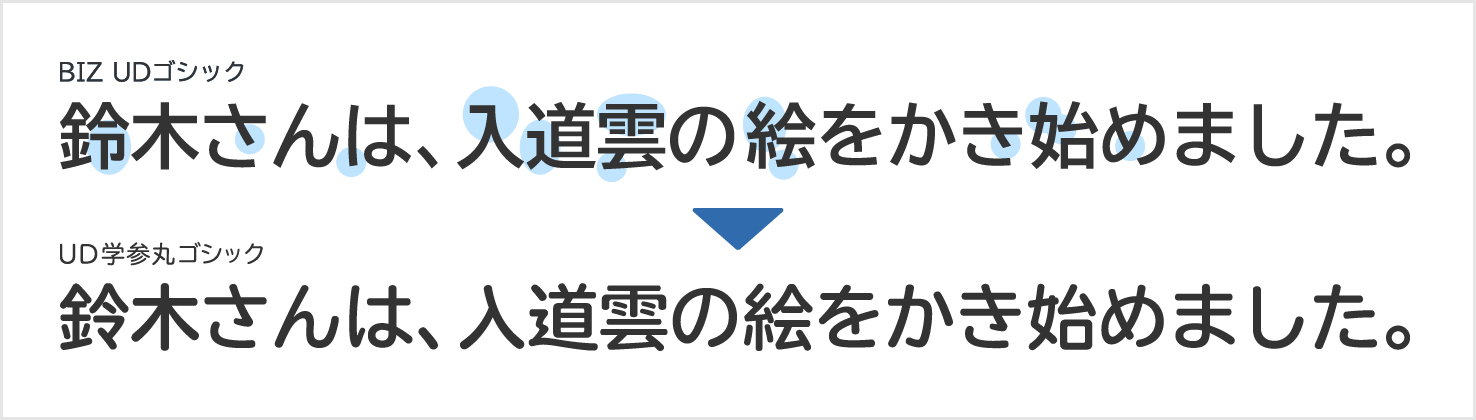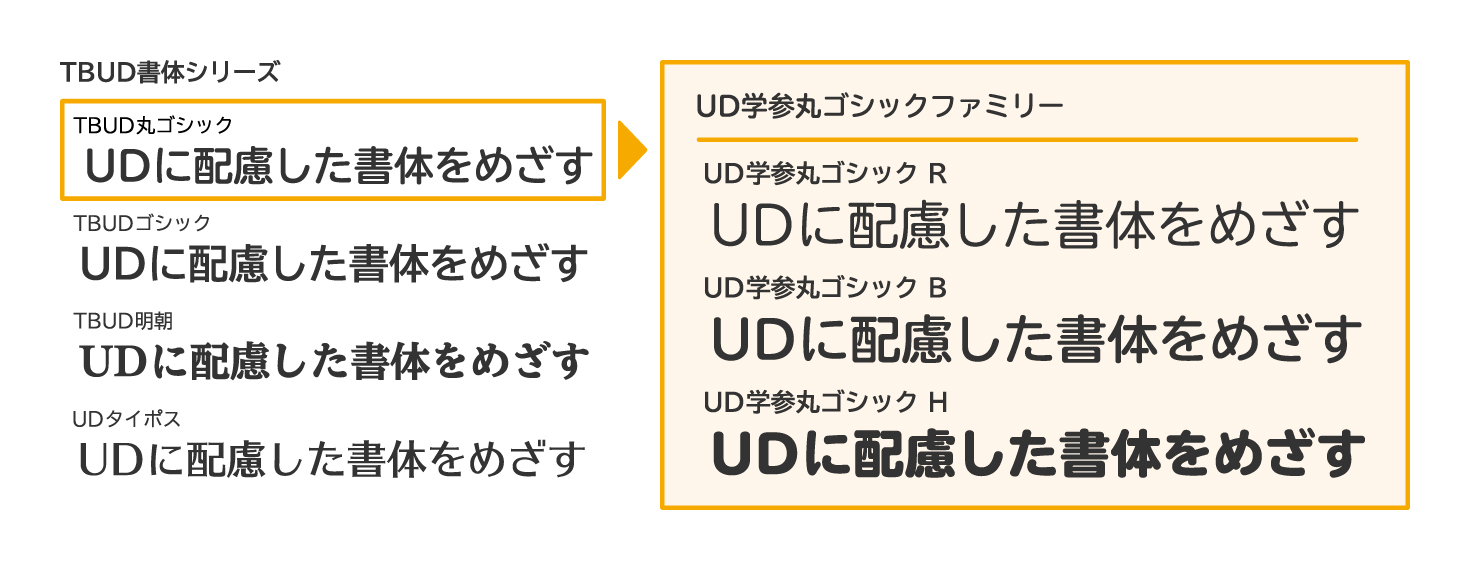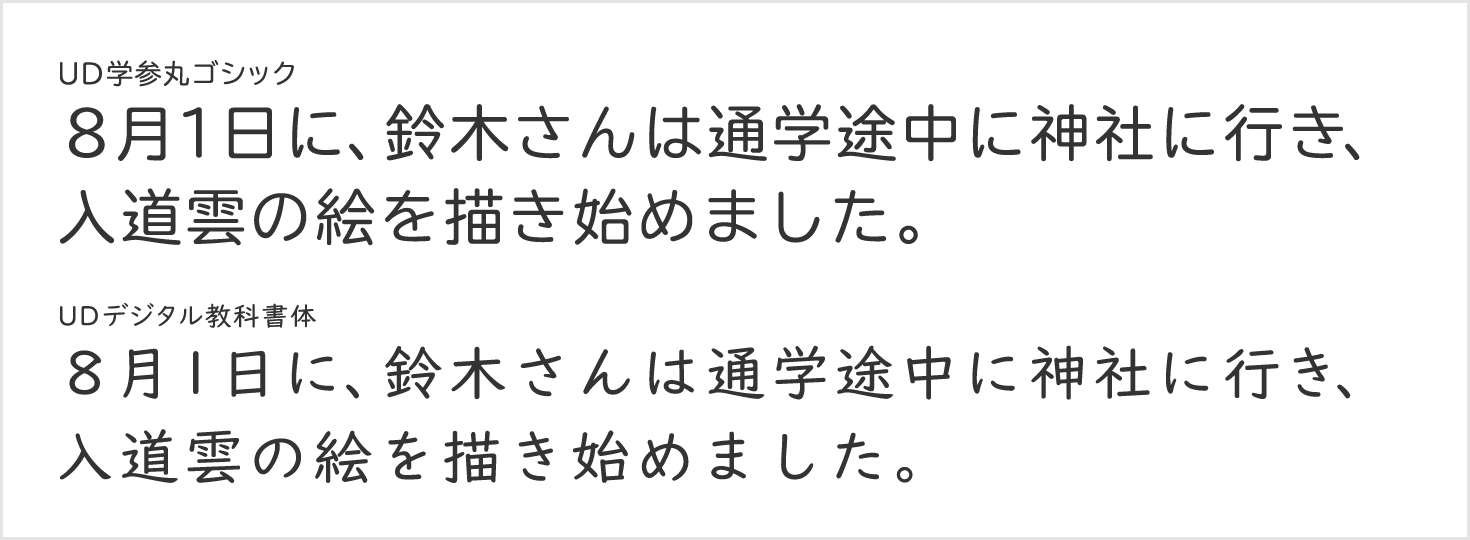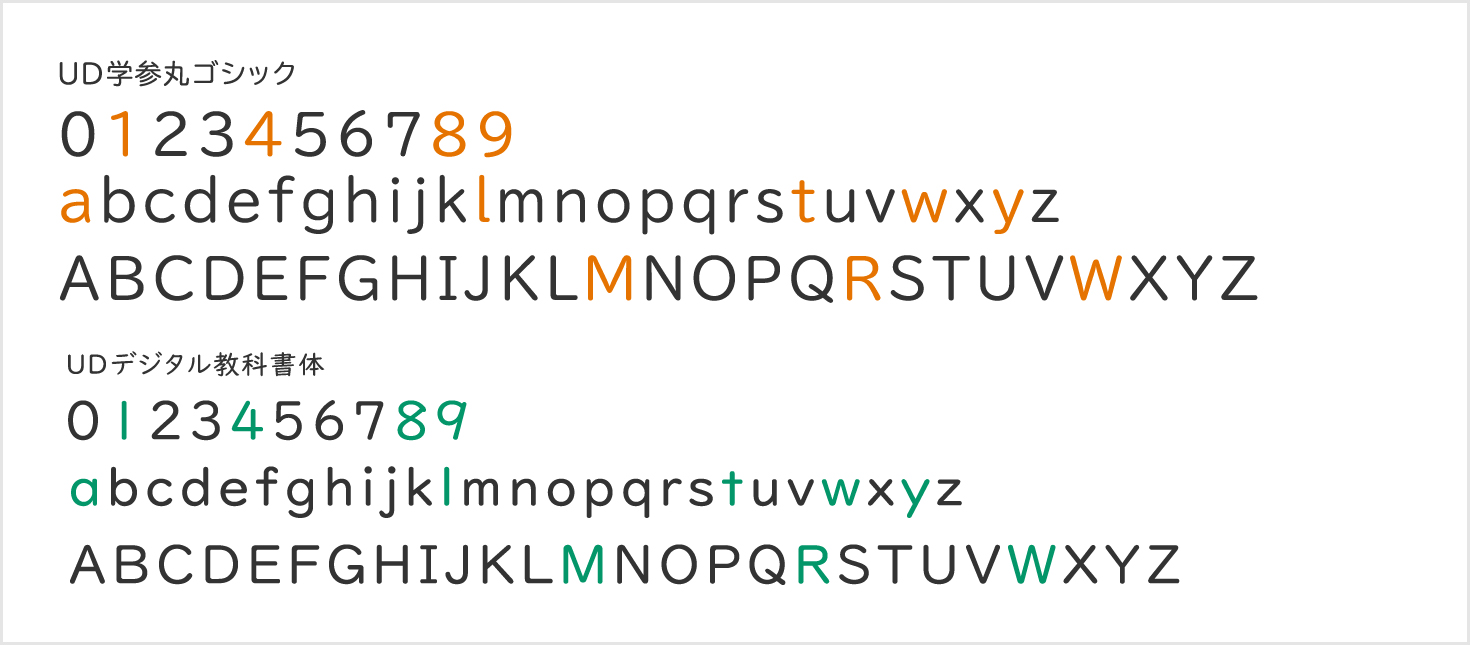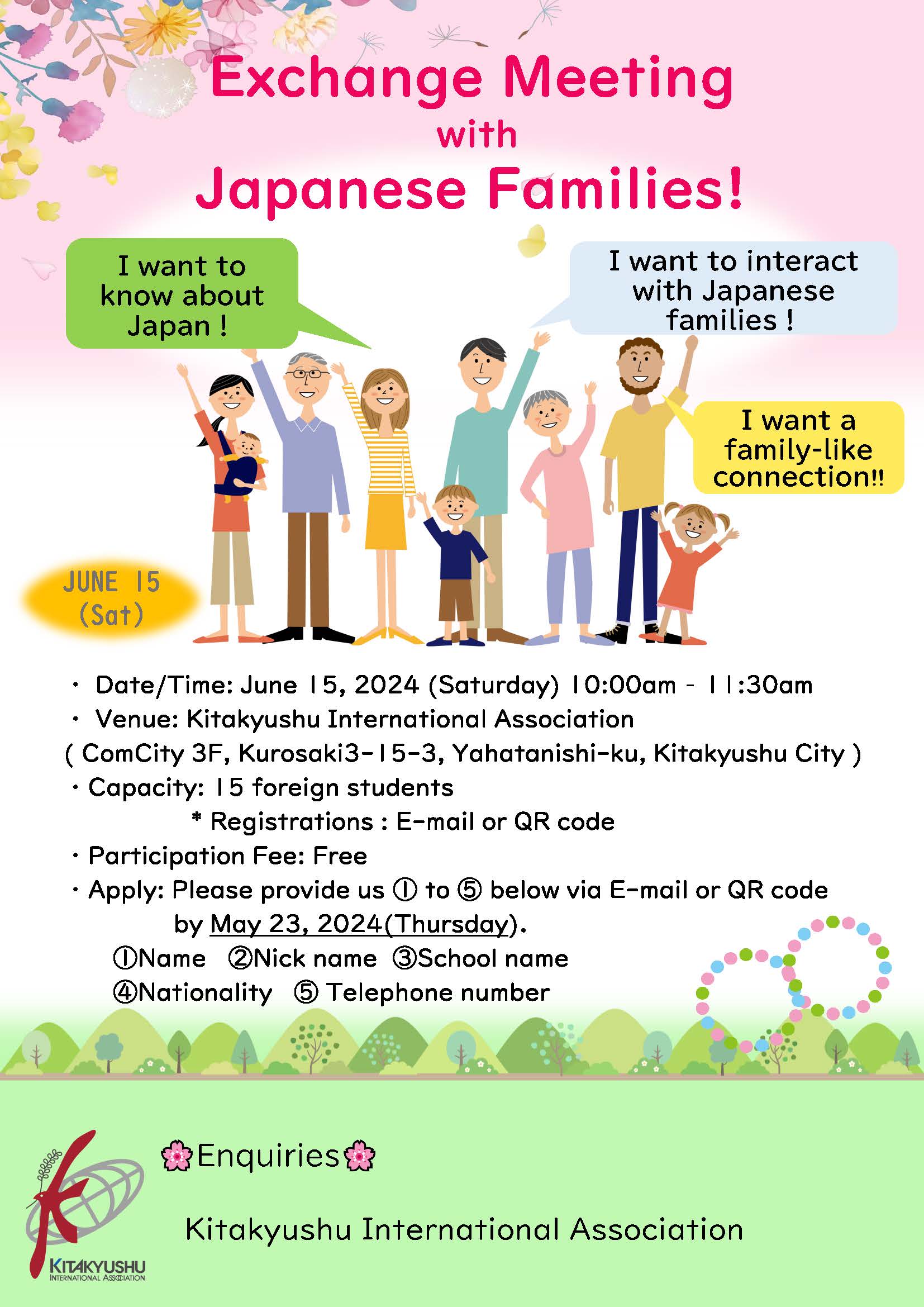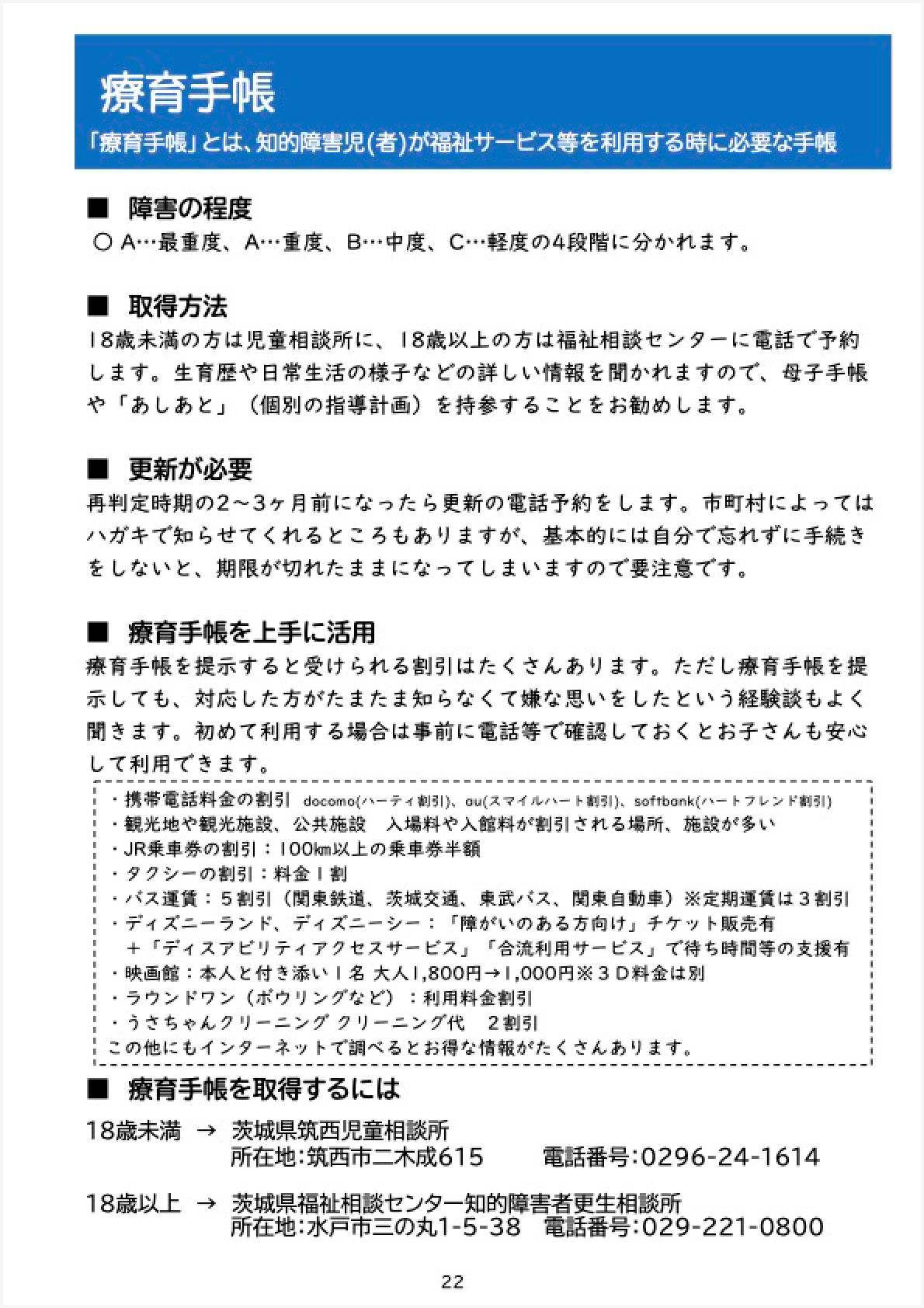
UD学参丸ゴシック R
UD学参丸ゴシック B
UD学参丸ゴシック H
UD学参丸ゴシックとは
「UD学参丸ゴシック」は、教科書・教材のために開発された丸ゴシック体です。全ての和文の文字が文部科学省の学習指導要領の字形に準拠(学参化)しているため、「UDデジタル教科書体」と並んで、読み書きに困難さのある児童・生徒を含む多くの子どもたちの学習を助ける書体です。子どもたちの発達段階や使用目的などに合わせて、「BIZ UDゴシック」「UDデジタル教科書体」など他のUDフォントと併用したり、使い分けていただくことが可能です。
学参化することで、視覚的に筆画がわかりやすいデザインにしています
読みやすさのエビデンス
「UD学参丸ゴシック」のベースとなった書体は、「TBUD丸ゴシック」です。 全国の視覚障害特別支援学校(盲学校)高等部18校の協力を得て、ロービジョン生徒90名を対象に面接調査を実施。 「中野泰志・新井哲也(2012). 弱視生徒用拡大教科書に適したフォントの分析 ロービジョン学会誌, 第12巻, 81-88.」 より引用
「TBUD丸ゴシック」は慶應義塾大学 中野泰志教授の協力を得て開発したTBUD書体シリーズで、ロービジョン(弱視)の検証でも高い評価を得ています。
「UD学参丸ゴシック」は教科書・教材制作でも利用される書体です。
全国盲学校調査
「TBUD丸ゴシック」より3ウエイト(R・B・H)を選び、 文字種や、等幅・P付・K付の構成などWindowsに搭載されている「UDデジタル教科書体」と同じ仕様のフォントとしてリリースします。デザインやウエイト(書体の黒み)は、「TBUDゴシック」ベースで、Office 製品に最適化した「BIZ UDゴシック」とも親和性があります。
UDデジタル教科書体との違い
和文について
「UD学参丸ゴシック」の和文は、ひと文字ひと文字が大きく見えるように作られており、お年寄りやロービジョンの方の読み間違いが少なくなるよう、細かな工夫が施されています。ロービジョンの検証でも評価が高いフォントです。
「UDデジタル教科書体」の和文は、初めて文字を学習する方向けに手書きの形状を重視し、書写のルールに沿って、書き順もわかりやすくデザインされています。手書き形状のためやや小ぶりに見えますが、文字と文字の間が適度に広く、ディスレクシア(読み書き障害)を含め、眼疾患がなく読み書きに困難さを抱える方からの評価が高いフォントです。
※ いずれも同じ文字サイズです
「UD学参丸ゴシック」の英数字は、ロービジョンの方へのヒアリングから読み間違えにくいことに焦点を当てた丸ゴシックの形状が優先されています。学校で習う形状とは異なりますが、「1」と「l(小文字エル)」や、「a」と「o」、「W」と「VV」などの読み間違いを減らす工夫が施されています。グラフや表組みの数字表記などにも適しています。
「UDデジタル教科書体」の英数字は、開発当時(2016年)の小中学校で習う形状に沿って作られており、数字の「1」は鍵なしの形状です。英字は「Ball & Stick体」と呼ばれる形状なので、ラインナップの欧文シリーズと合わせてのご利用をおすすめしています。
※ いずれも同じ文字サイズです
UD学参丸ゴシックに関するアンケート調査
福岡教育大学にて、学生約273名を対象としたアンケート調査を実施いただきました。
その結果、4割以上の学生が「UD学参丸ゴシック」が、最もアルファベットと数字の形がはっきりわかると回答しました。
教育現場で活躍されている方々が、実際に「UD学参丸ゴシック」を活用いただいた事例をご紹介します。
特別支援教育や外国人留学生に対する情報など、幅広い分野で活用いただいています。
「UDデジタル教科書体」は、昨今の教育市場において広く話題となり、多くのメディアに取り上げられていますが、UDフォントにも明朝・ゴシックなど色々な種類があり、子どもたちにとって読みやすい書体は「UDデジタル教科書体」一択ではありません。今回、学校現場でも使用しやすい仕様で、学習指導要領に準拠した新しいバリエーションが増えたことで、モリサワが目指すユニバーサルデザイン、つまり「対象者や目的によって様々な選択肢が用意された環境」を実現する上でも、広く貢献できるのではと思います。
例えば、ロービジョンの子どもを対象に、文字を取得する段階では、「UDデジタル教科書体」を大きく表示し、書き順や手書きの形状を学習してもらい、文字を取得した後は、ひと文字ひと文字が大きく表示できる「UD学参丸ゴシック」で、対象者の読みやすい大きさで文章を表示し読みやすくすることも可能になります。